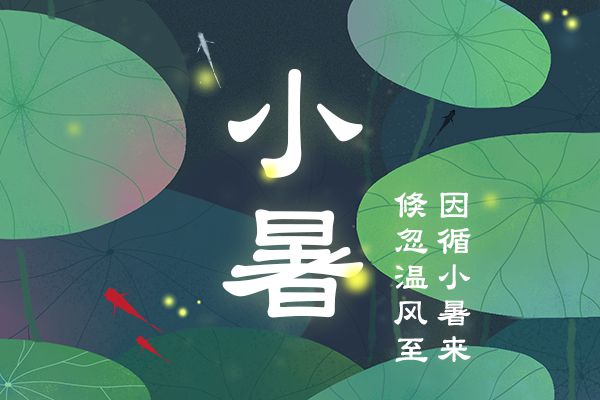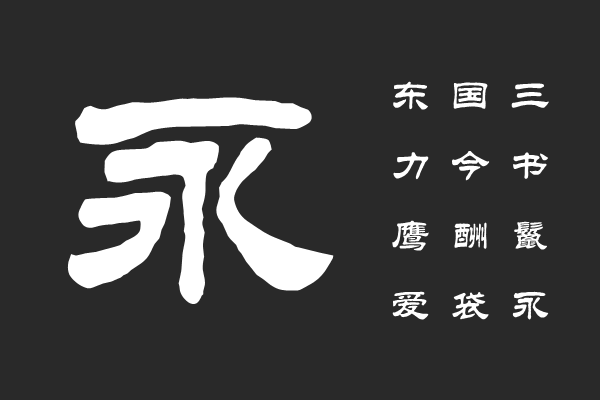
隶书字体大全,8款隶书字体分享
隶书的出现,标志着汉字从古老的线条化、象形化向更成熟、更规整的方块字迈进,为后来的楷书、行书、草书奠定了基础。如果你正在找一些比较不错的隶书字体,本文就会给你推荐几款,帮你更好更快的使用隶书字体。
隶书有哪些特点
- 古朴典雅
隶书的书写,带着一种古老而沉静的气息,能够瞬间将我们带回那个遥远的时代,感受到历史的厚重感。
- 端庄大气
扁方的字形和舒展的笔画,使得隶书显得端庄而大气,非常适合用于需要展现庄重、威严或历史感的场合。
- 装饰性强
蚕头燕尾、波磔等独特的笔画处理,使得隶书具有很强的装饰性,能够为设计作品增添独特的视觉韵味。
8款隶书字体分享
临海隶书
临海隶书是一款传统风格的隶书字体,笔画端庄有力,适合标题、标语和需要传统气质的设计场景。隶书风格明显,横画宽竖画短,笔画带有传统气息,字形结构紧凑,适合标题与短文案。这款是免费商用的隶书字体,关注的小伙伴会比较多。
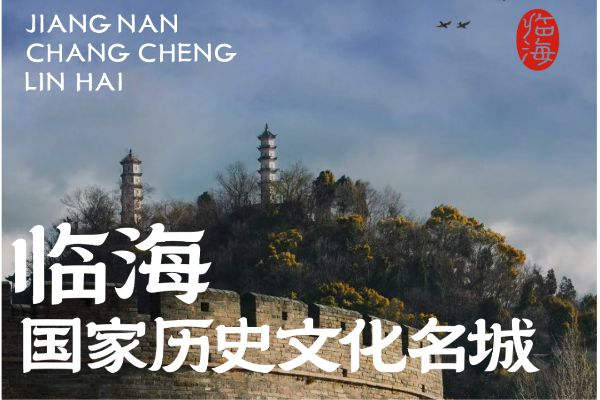
使用场景:
- 海报标题、活动横幅、文案标语
- 传统文化主题的出版物及包装设计
- 商业广告中的强调文本与标题
华康隶书体
华康隶书体是一款经典的隶书风格中文字体,笔画端庄、结构紧凑,适合作为标题和强调文本使用。笔画分布均衡,横竖对比鲜明,字形圆润,具有良好的可读性。
使用场景:
- 招贴、宣传册标题
- 商业包装、海报和海报细文
- 品牌形象中的强调文本
汉仪中隶书
汉仪中隶书是一款现代化的隶书字体,笔画干净、结构紧凑,适合标题与标注性文本。风格清晰,笔画对比明显,字形紧凑,适于小段文本的排版。
使用场景:
- 宣传单页标题、海报大字
- 品牌宣传文本、包装标签
- 信息图中文字标注
汉仪范笑歌隶书
汉仪范笑歌隶书是一款具有风格化隶书特征的字体,能快速传达情感与风格,与简洁正文搭配时视觉层次明显。
使用场景:
- 活动海报标题、促销文案
- 品牌宣传材料中的重点文本
- 社交媒体封面与图文标题
点字小隶书
点字小隶书是一款带有点状装饰的隶书风格字体,适合用于标题、海报和设计元素的点缀文本。点字小隶书可以突出个性与装饰性,提升视觉冲击力,与简约正文搭配时层次分明。成为字由会员,就可以免费商用。
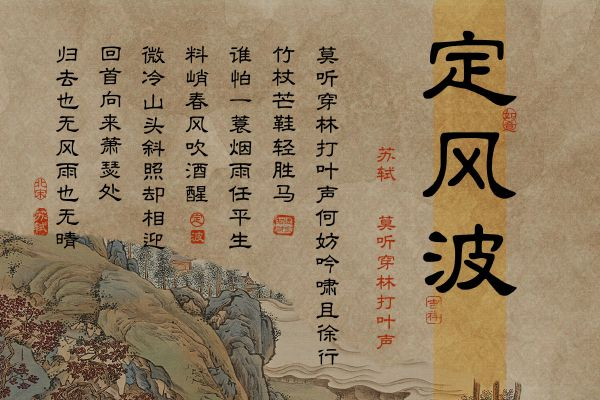
使用场景:
- 标题、横幅、促销文案
- 活动海报的重点文本
- 品牌宣传材料中的装饰性文字
Aa烈焰隶书
Aa烈焰隶书是一款具有烈焰感与隶书风格的装饰字体,线条粗细对比强烈,带有火焰式笔触变化。字形轮廓鲜明,适合制造视觉冲击,在大字号标题中表现尤为出色。
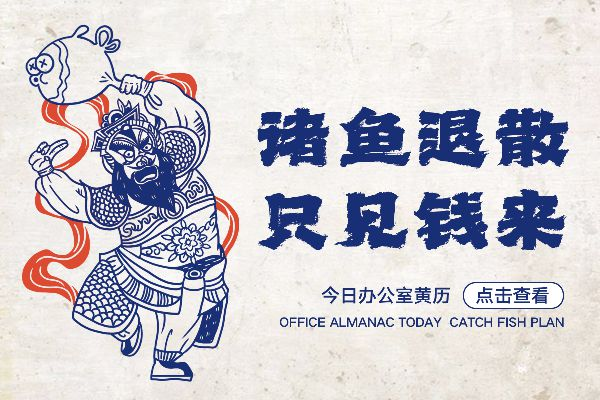
使用场景:
- 主题海报、促销广告、社媒图文标题
- 品牌宣传材料的重点文本
- 活动横幅与开场标题
Aa放放隶书
Aa放放隶书是一款带有轻松动感的隶书风格字体,横竖线条对比鲜明,笔画带有轻微放射感。风格活泼,易于塑造亲和品牌形象,与简约正文搭配时具备良好层次感。
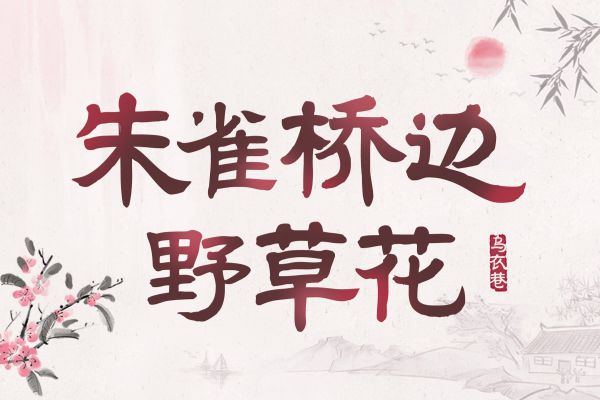
使用场景:
- 标题、海报与活动海报细文
- 品牌宣传材料中的重点文本
- 社交媒体封面与图文标题
字悦毛笔隶书
字悦毛笔隶书是一款结合毛笔笔触与隶书风格的字体,毛笔效果与隶书轮廓结合,笔画自然摆动,字形端正,适合中等及大字号标题。
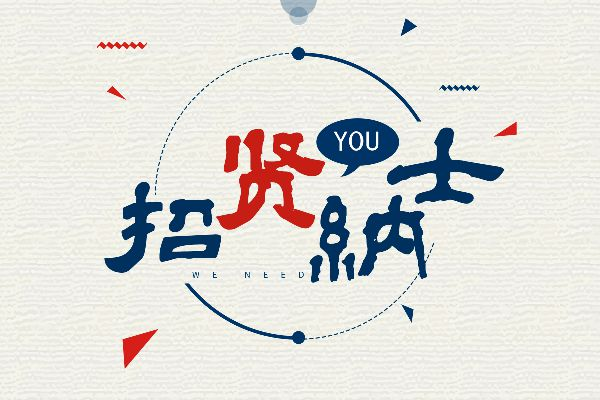
使用场景
- 文化活动海报、书法主题设计
- 品牌推广文案中的标题与强调文本
- 书籍、海报及展览宣传材料
总结隶书字体应用场景
尽管隶书具有很强的艺术性,但在作为正文使用时,其可读性可能不如楷书或宋体。因此,在设计中,通常将隶书作为标题、装饰性文字使用,而正文则选择更易读的字体。
另外隶书的风格比较鲜明,在与其他字体搭配时,需要注意风格的协调性。通常,隶书与一些古朴、典雅的字体搭配效果较好。
隶书比较常见的使用场景如下
- 一些茶庄、古董店、书法工作室等品牌标志与VI设计。
- 具有复古风格、文化气息的海报、需要突出庄重、典雅主题的宣传资料
- 历史剧、古装剧的片头片尾,以古代为背景的游戏
- 书法艺术创作